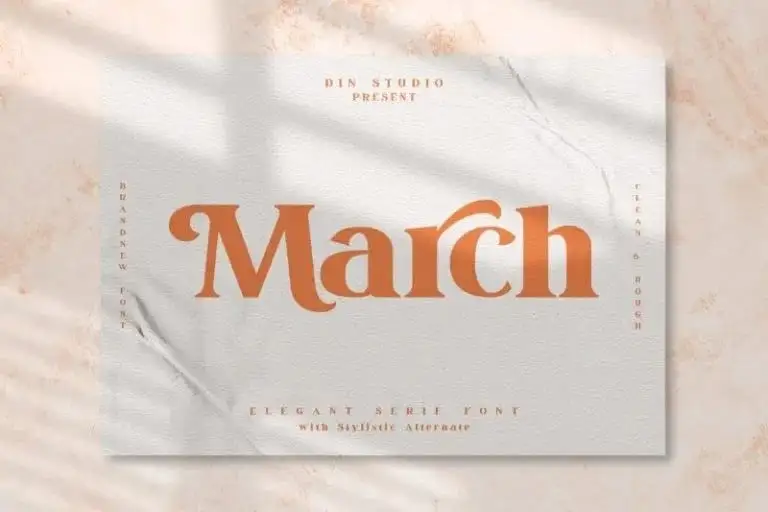
A March Serif Font é uma seleção de fontes que captura o espírito moderno e vintage de um design que se destaca entre as outras. Com seu estilo contemporâneo, mas com um toque vintage marcante inspirado em marcas antigas, a March Serif está certa para revolucionar sua identidade visual. Criada pelo designer Din Studio no site 99designs, esta fonte é perfeita para quem busca uma sensação única de elegância clássica e contemporaneidade na linguagem do seu trabalho. Uma das suas características mais distintivas é o seu toque vintage que adiciona um sabor nostálgico a qualquer design. Mesmo em projetos simples como nomes de empresas, logotipos ou templates de impressão, a March Serif traz uma dose de originalidade que vai fazer sua marca ser lembrada. A March Serif é um verdadeiro complemento para designers que buscam adicionar um toque especial e único aos seus trabalhos. O designer dinâmico da Din Studio fez deste fonte uma escolha irresistível, criando uma variedade moderna e limpa que se adapta facilmente a qualquer projeto. A March Serif é uma opção ótima para aqueles buscando um design sofisticado, mas também interessante, tornando-a uma excelente opção para todos os tipos de projetos digitais ou impressos. Além disso, a fonte está disponível em versões suaves e mais agressivas. Essa ampliação é ideal para quem deseja criar diferentes níveis de resolução em seus trabalhos – seja num design digital criativo ou no ambiente de impressão. A March Serif é uma escolha inteligente para qualquer designer que procura uma fonte moderna e vintage que se destaca, deixando um impacto duradouro.